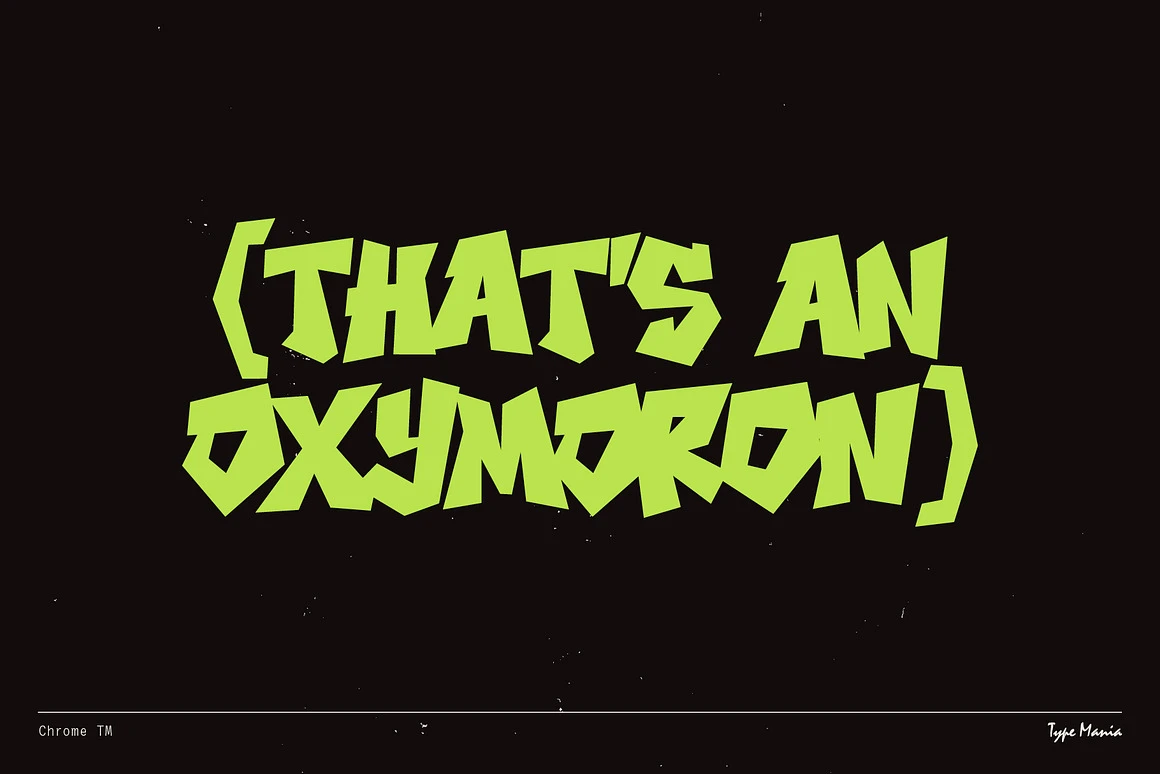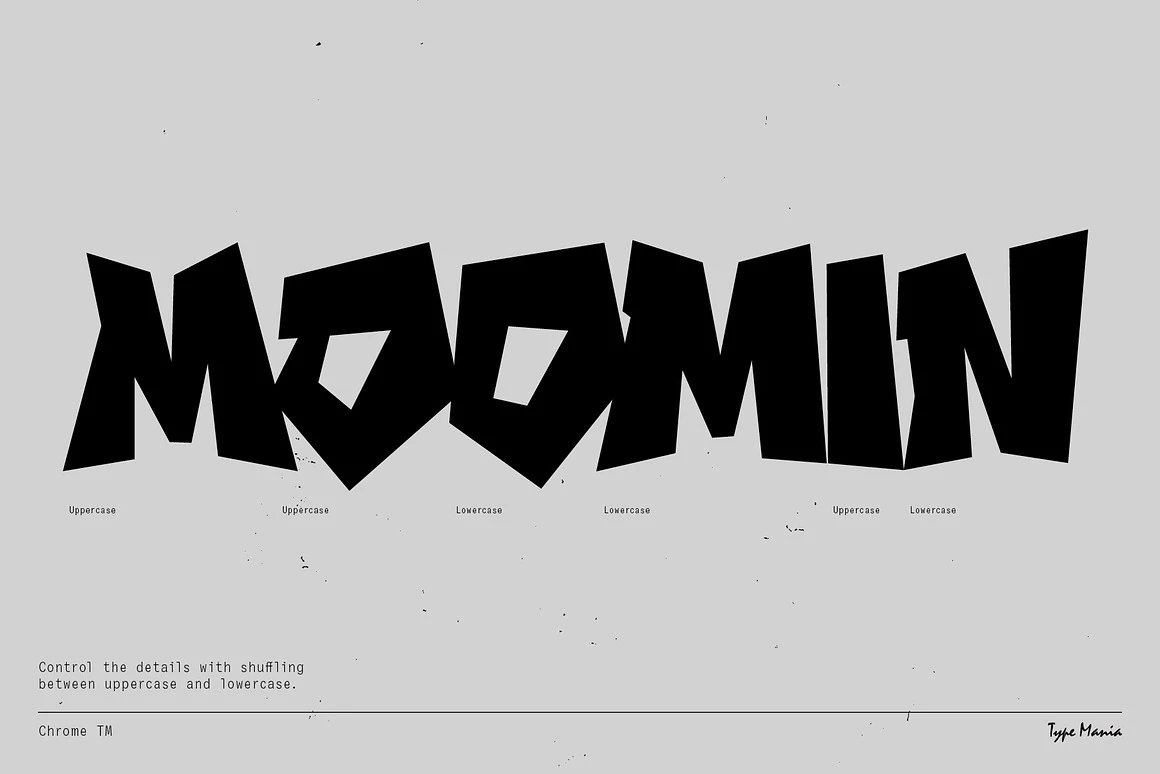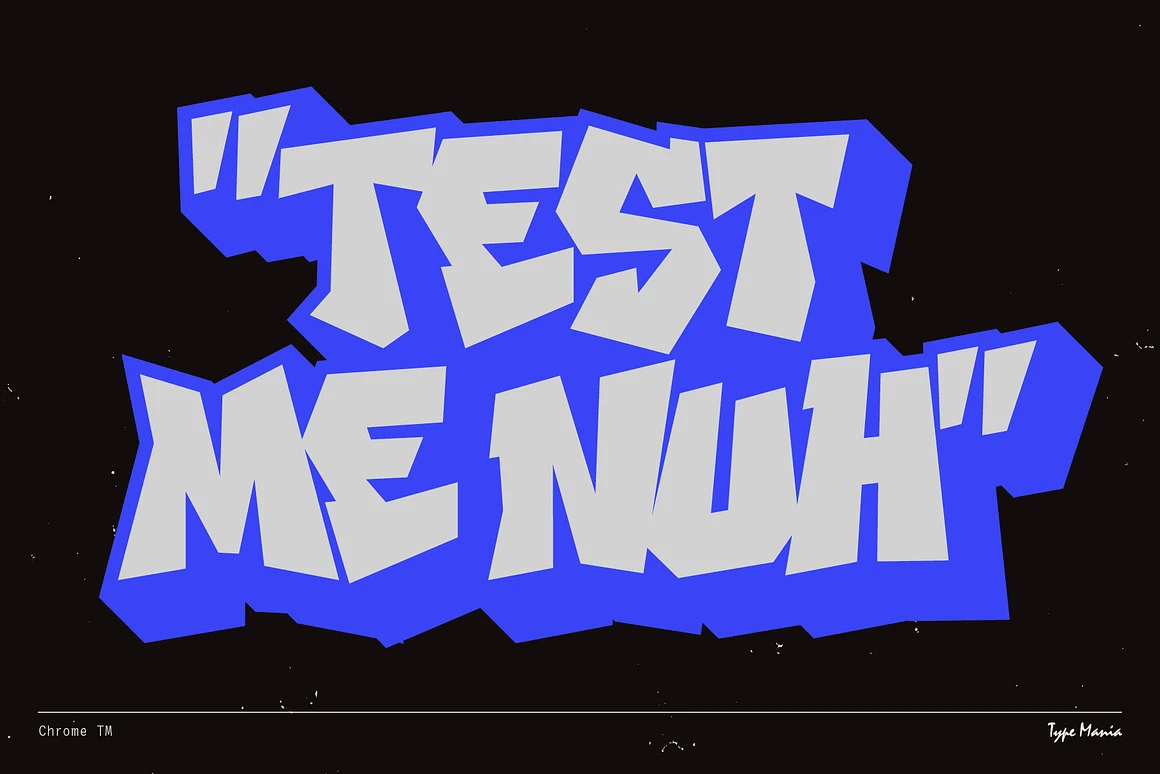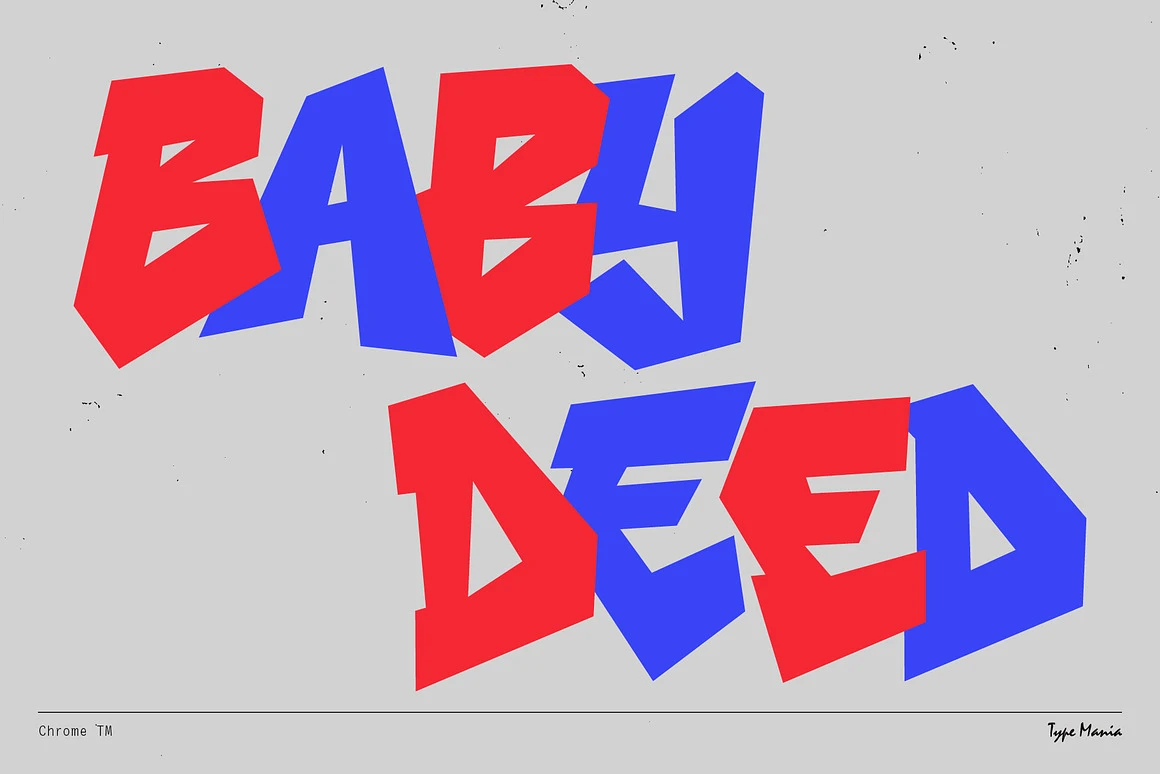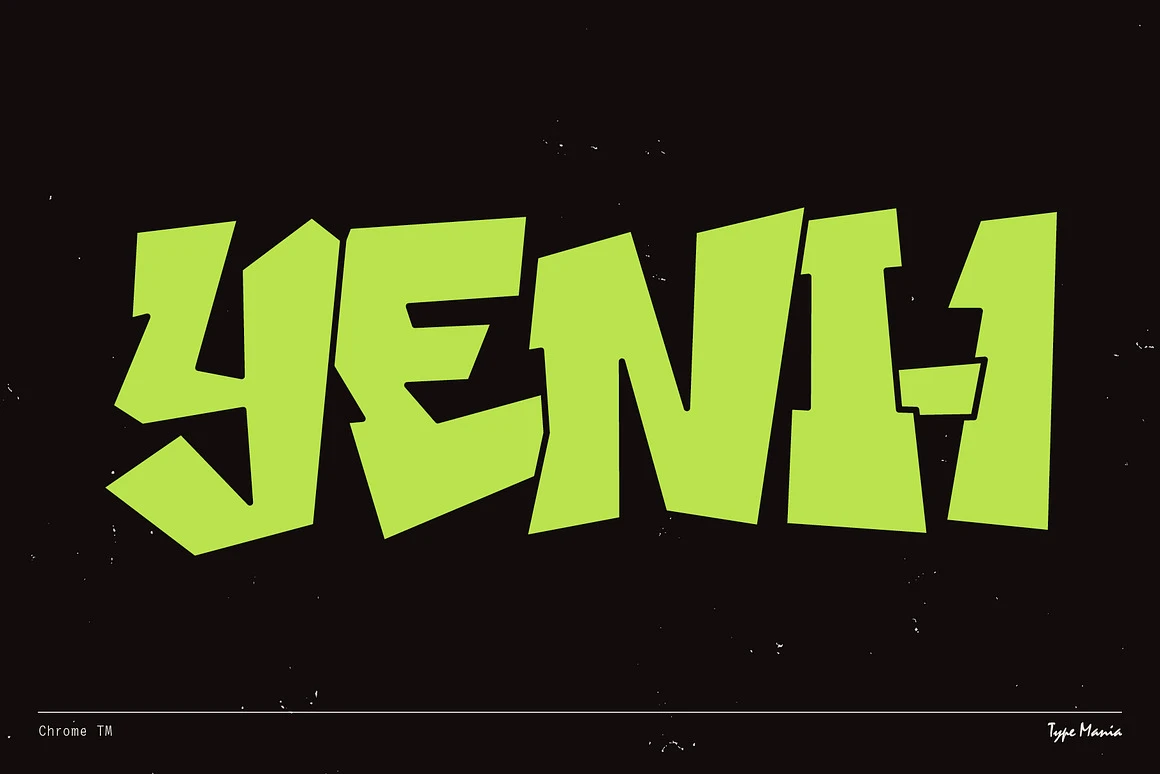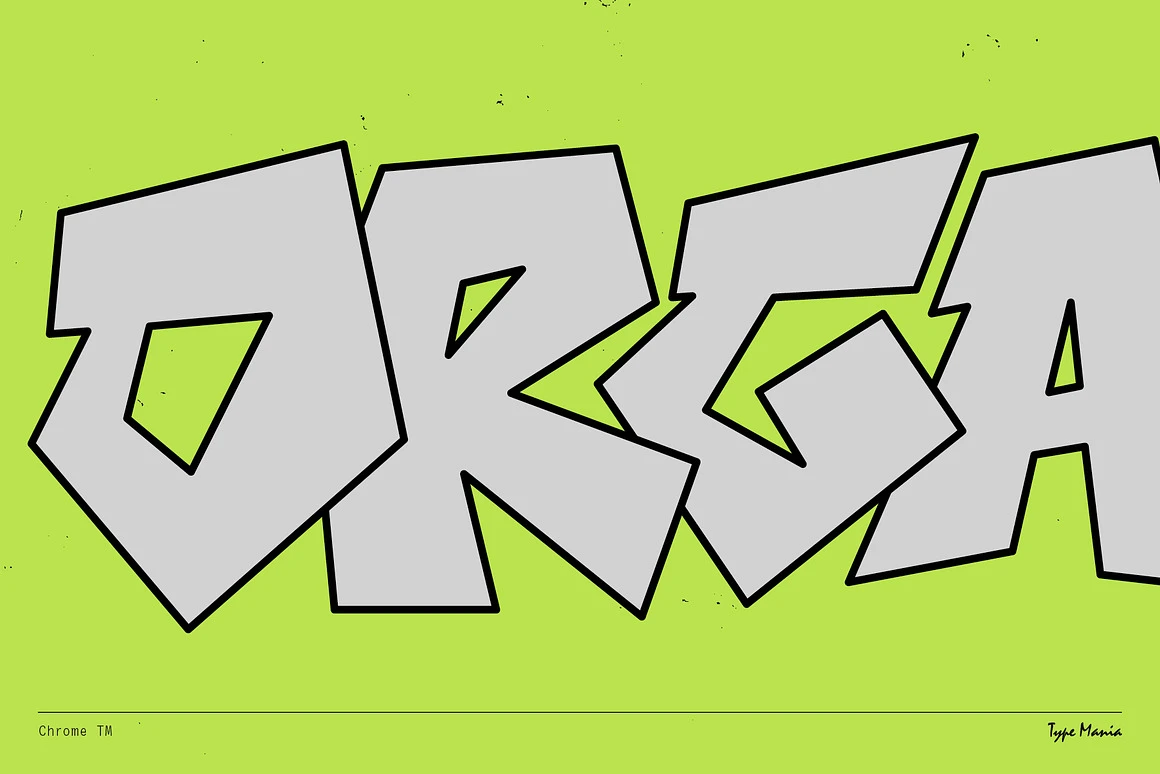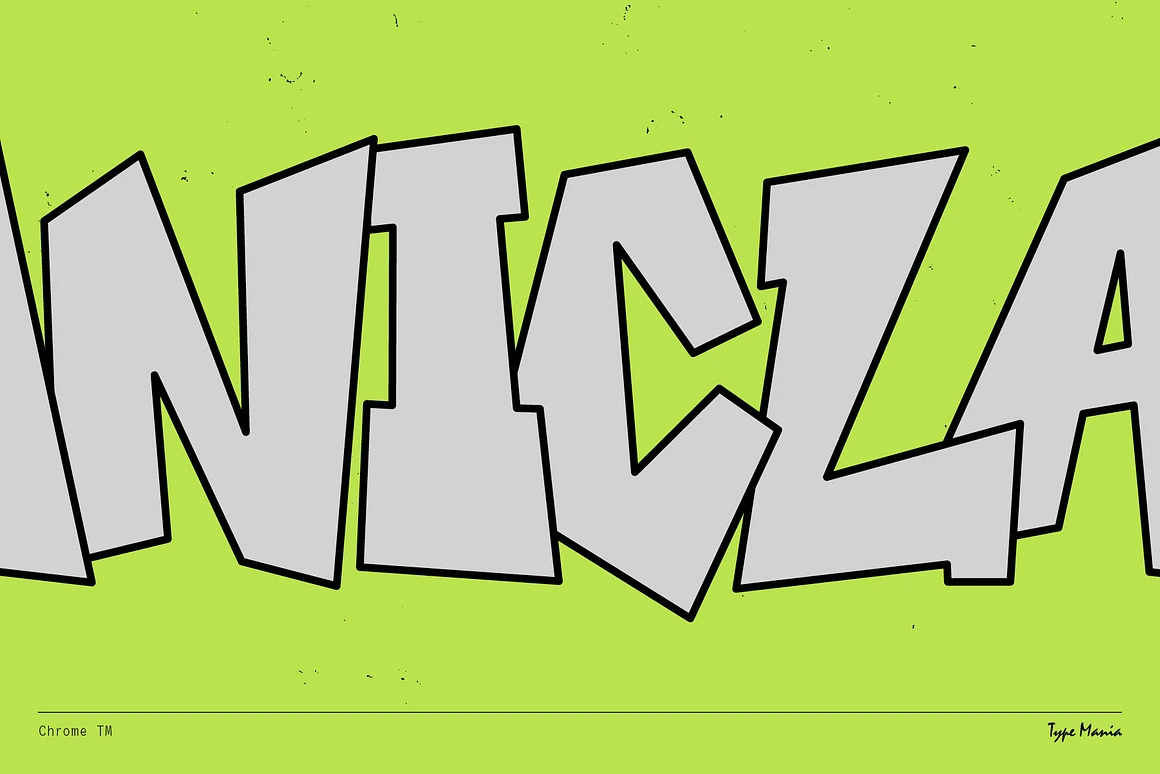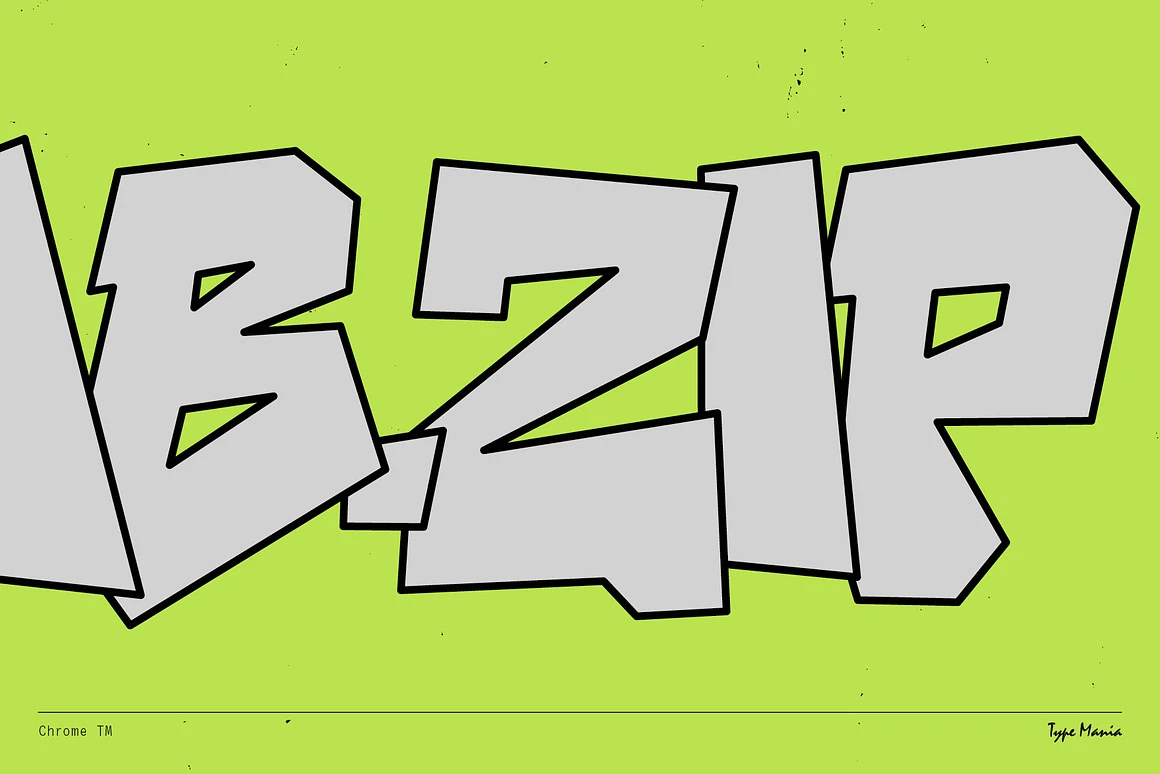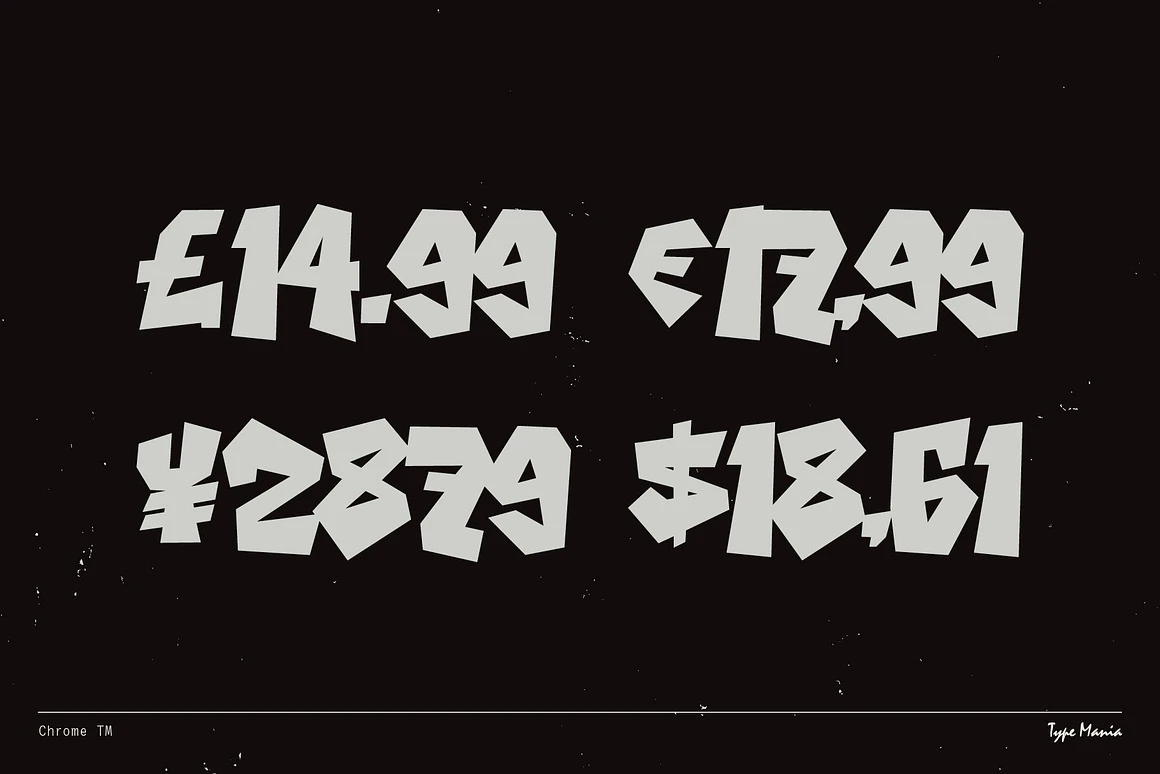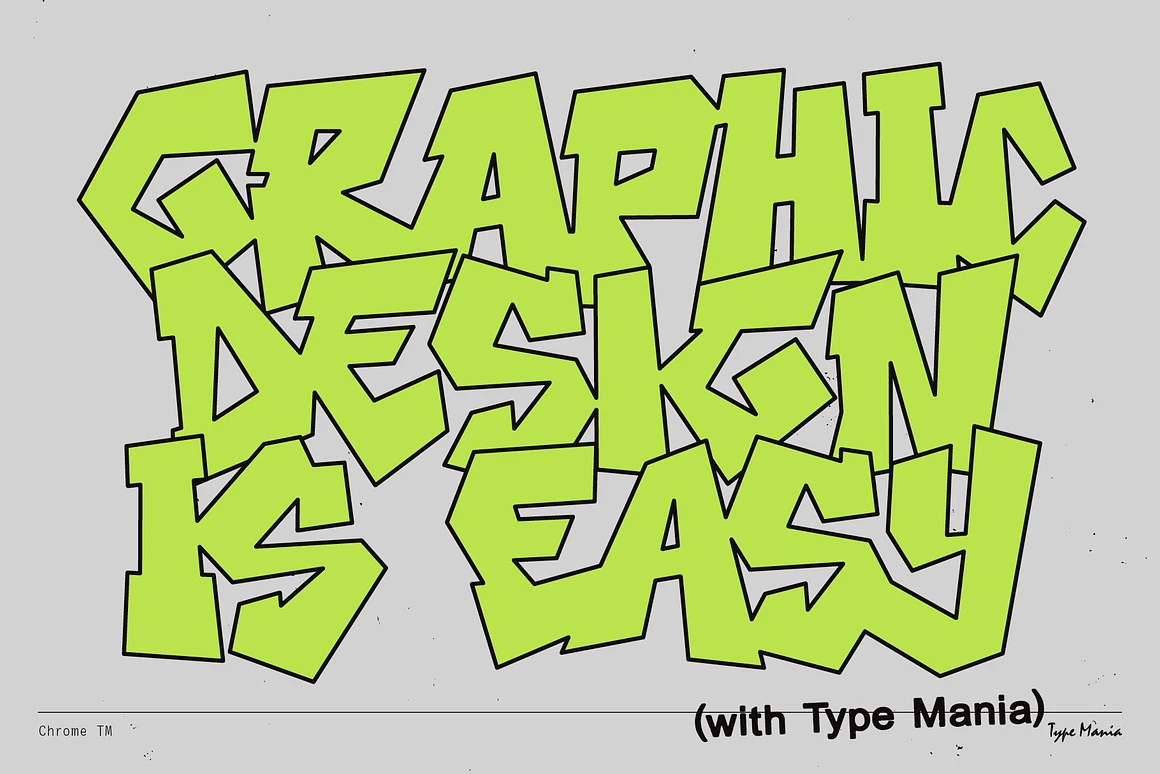
Này nè: Chrome TM – một font chữ đậm, đô thị được lấy cảm hứng từ phong cách chữ graffiti. Tuyệt vời cho việc thiết kế thương hiệu, poster, bìa album, trang phục… và nhiều thứ khác nữa. Hãy thử sử dụng và xem nó có phù hợp với dự án của bạn không.